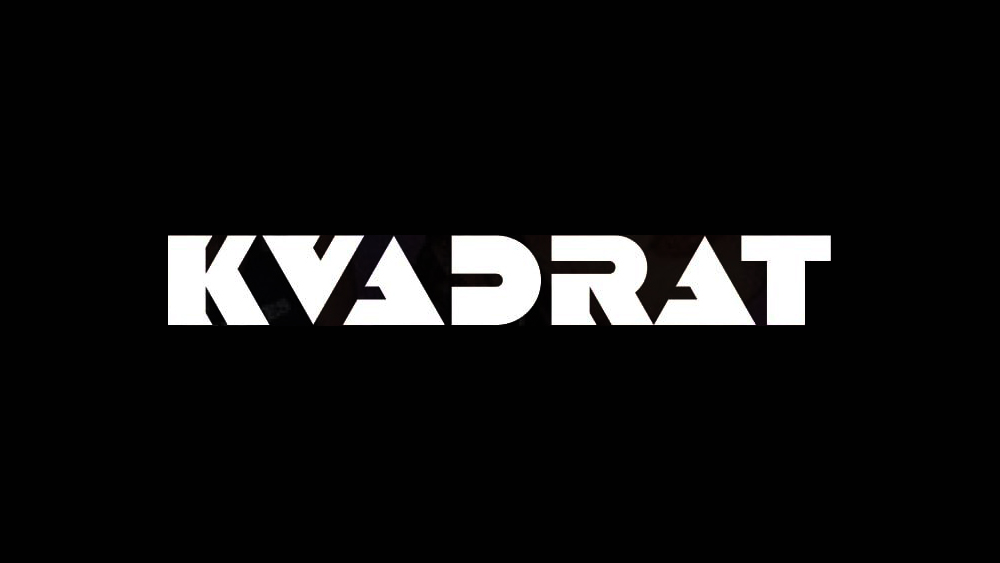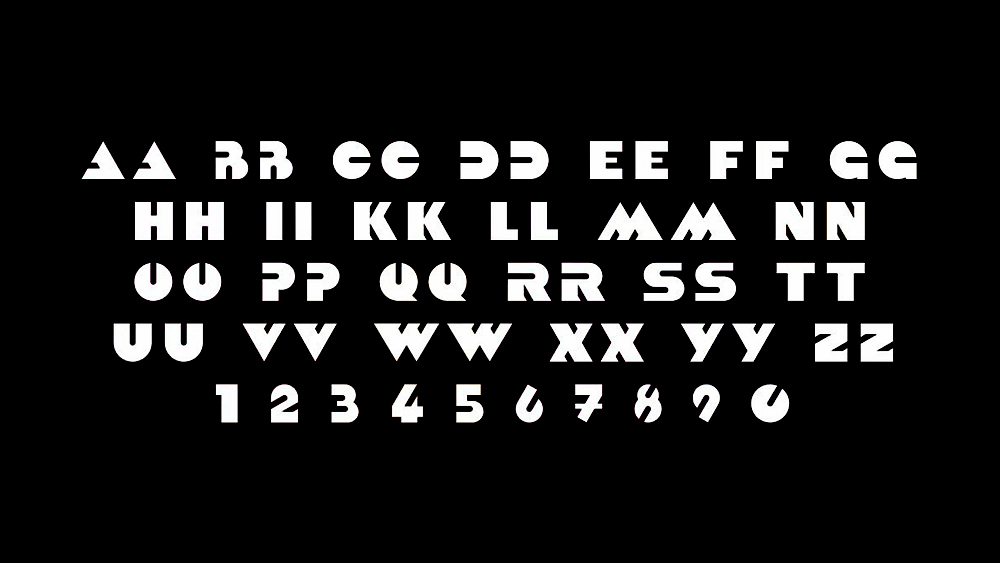
دانلود فونت انگلیسی Kvadrat Font
فونت پرمیوم و انگلیسی Kvadrat Font یک فونت عالی برای پروژه برندسازی مانند نام تجاری، لوگو، تیتر و سرفصل و… مناسب است.
مزایای استفاده از فونت لاتین Kvadrat چیست؟